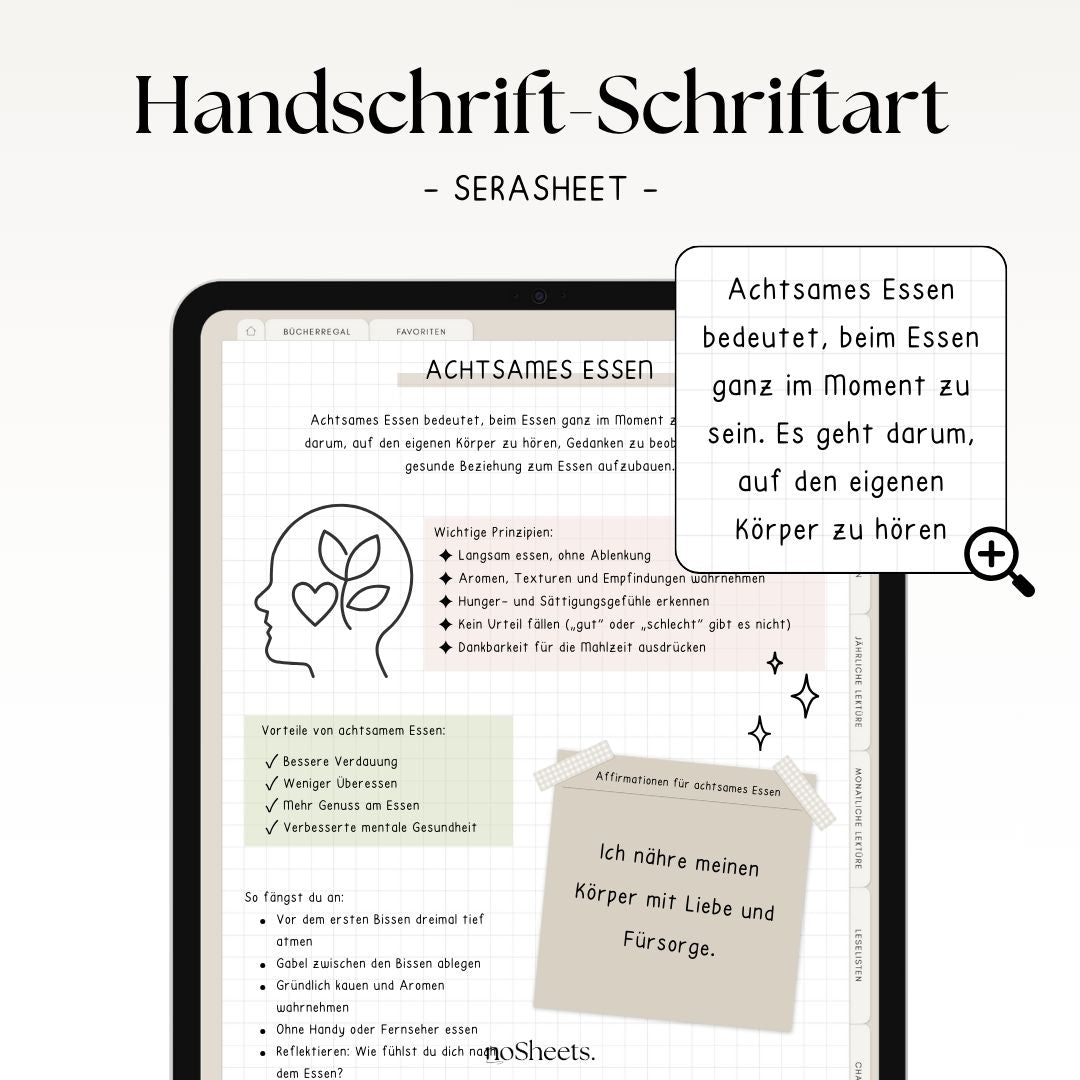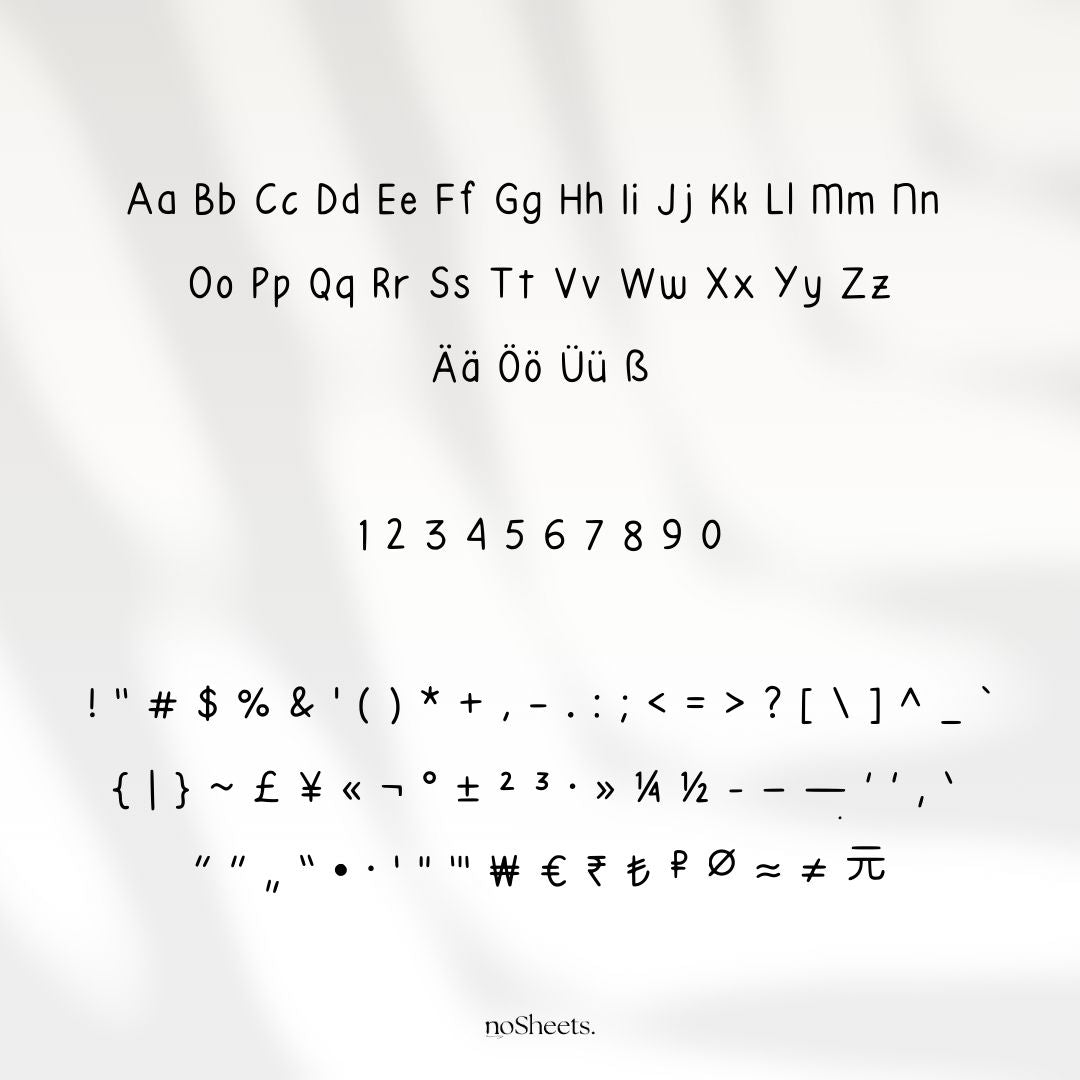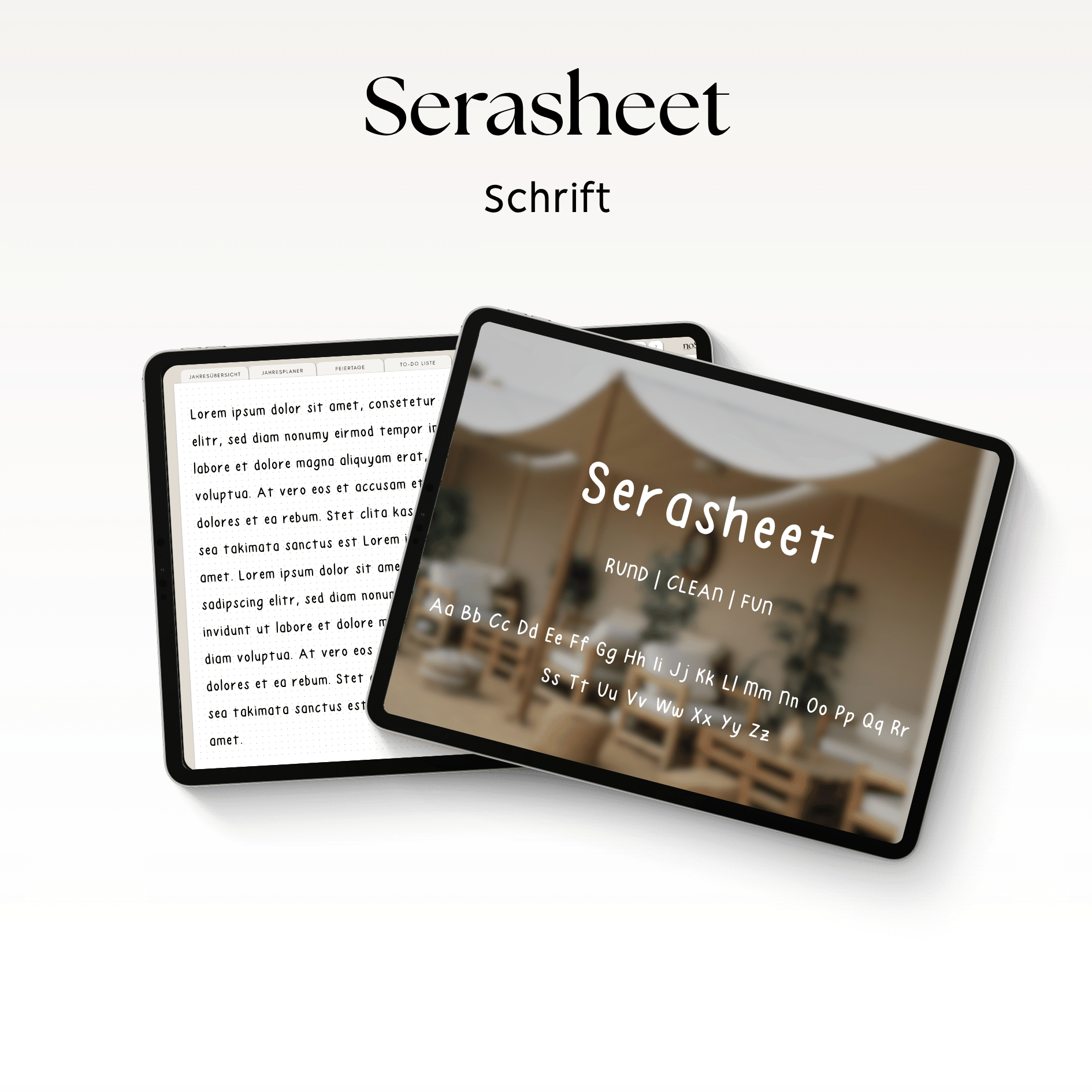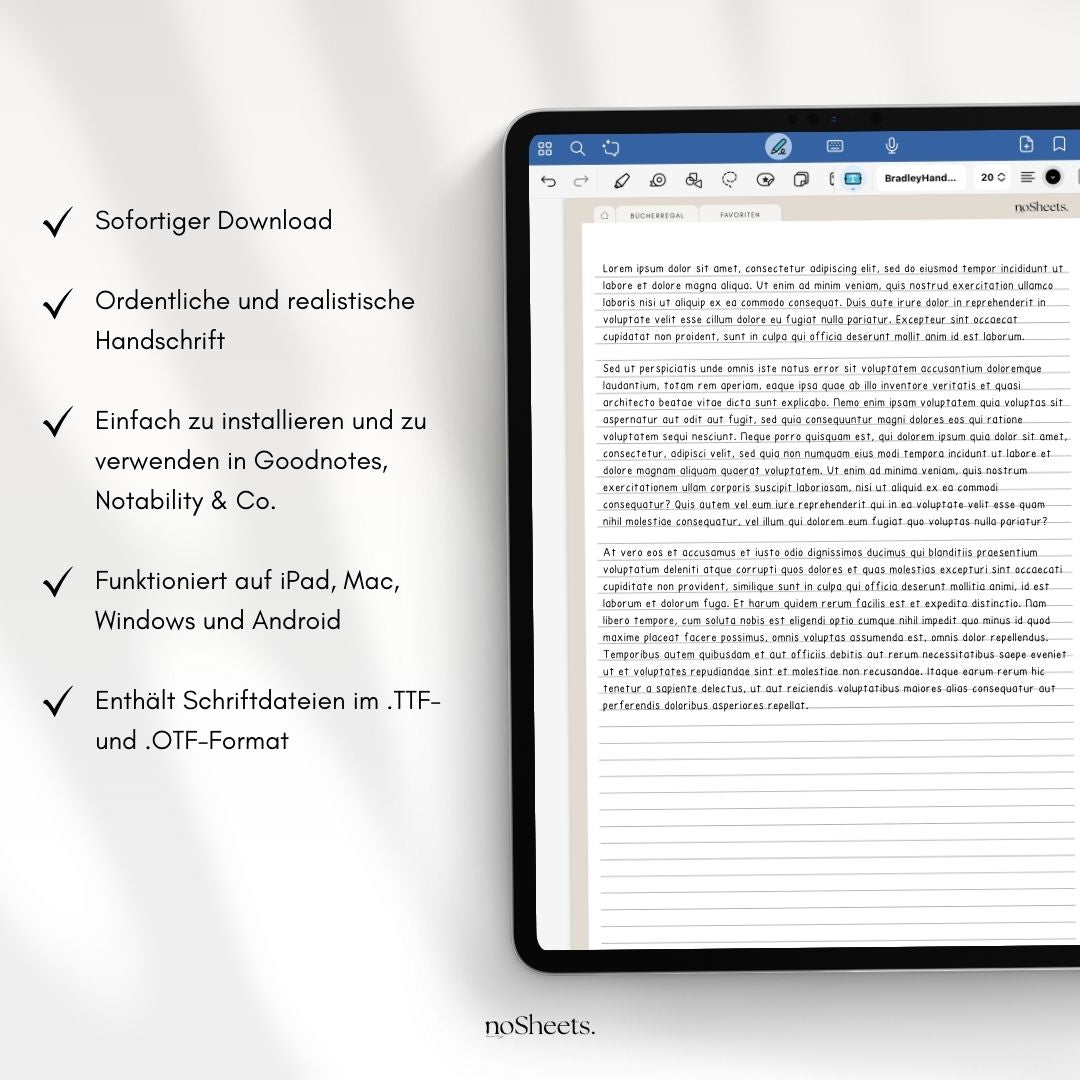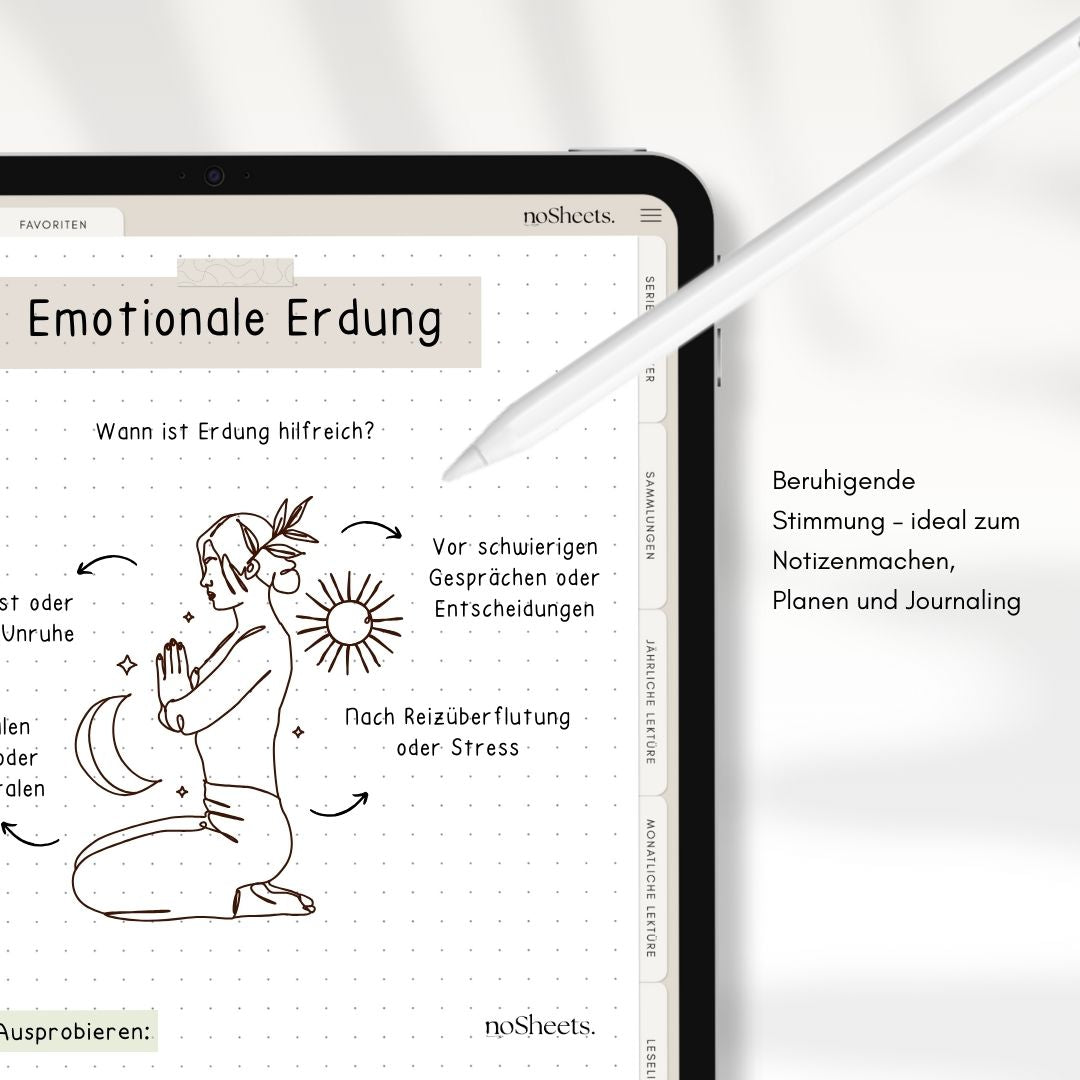
Font | Serasheet
Serasheet – Deine digitale Handschrift, zum Strahlen gebracht
Warm. Persönlich. Charmant.
✓ Authentischer Handschrift-Look
Jeder Buchstabe wirkt so, als wäre er liebevoll mit dem Stylus gezeichnet – persönlich, charmant und immer herzlich lesbar. Ideal, um deinen digitalen Planern, Notizen oder Titeln Persönlichkeit zu verleihen.
✓ Rund & verspielt – trotzdem modern
Die Formen strahlen durch ihre weichen Rundungen eine verspielte Leichtigkeit aus. Doch trotz dieses verspielten Charmes bleibt Serasheet stets klar und elegant – perfekt für strukturiertes Design mit einem Hauch Kreativität.
Perfekt für…
✓ Digitale Planer und Scrapbooks
✓ Handgeschriebene Titel & Anmerkungen
✓ Persönliche Designs: Einladungen, Grüße, Social Media